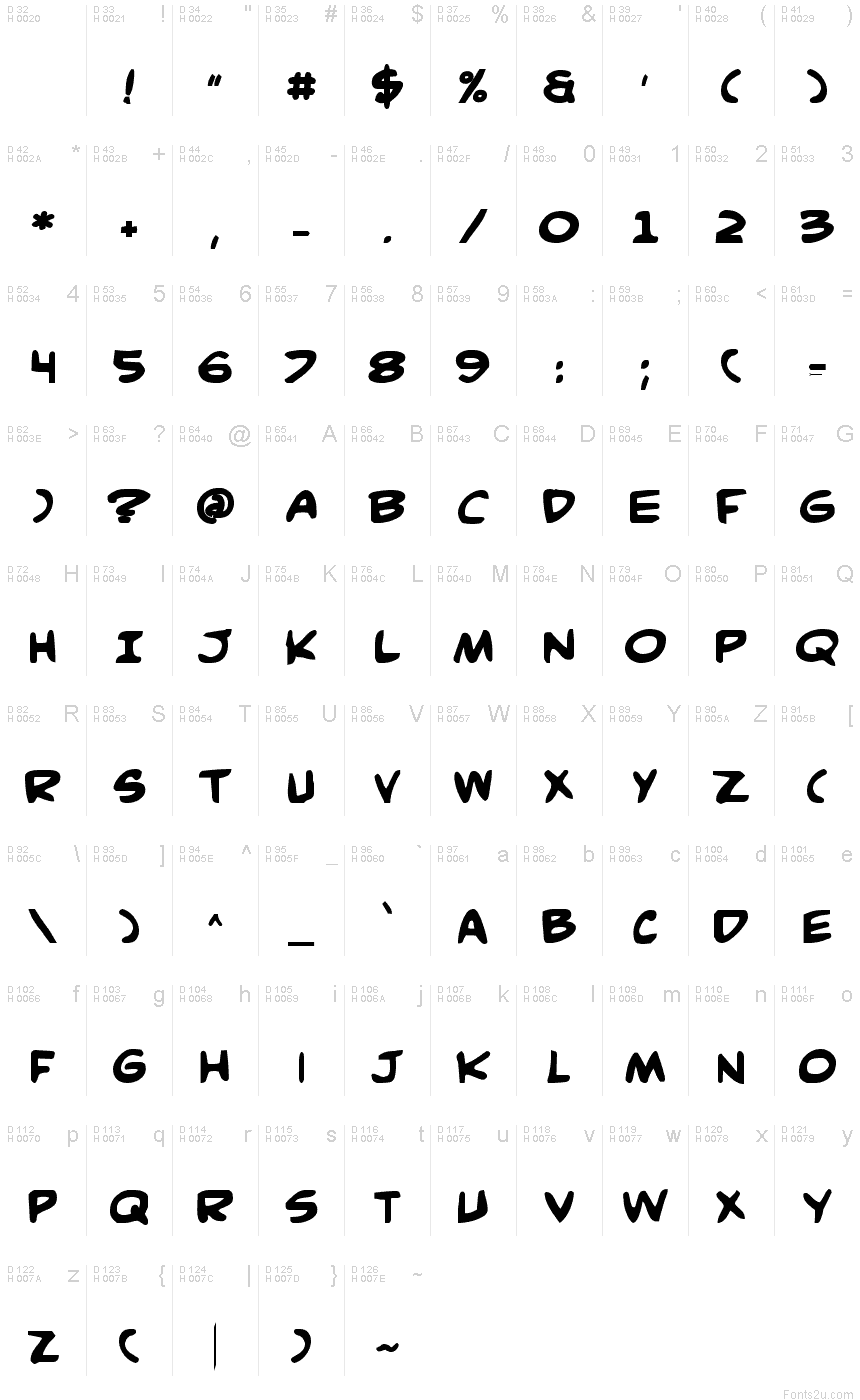
Comic Book Commando Bold
Font Comic Book Commando Bold od Iconian Fonts uderza grubymi, tuszowanymi kształtami i żywym rytmem, który przywodzi na myśl dymki z komiksów. Ciężkie krzywe i nieco nierówne szerokości nadają mu ręcznie rysowaną energię „POW”, nie tracąc przy tym czytelności, dzięki czemu nagłówki pozostają wyraźne nawet przy powiększeniu. To darmowy font typu display w stylu komiksowym.
Comic Book Commando Bold świetnie sprawdza się na okładkach komiksów, w logo superbohaterów, zaproszeniach na przyjęcia dla dzieci, plakatach w stylu arcade, zestawach naklejek, miniaturach na YouTube i wyrazistych grafikach do mediów społecznościowych. Ustaw nieco luźniejsze światła, aby czarna masa mogła „odetchnąć” i połącz go z neutralnym krojem bezszeryfowym w podpisach i napisach – ten darmowy font zadba o efektowny wygląd, podczas gdy towarzyszący mu krój zajmie się detalami.